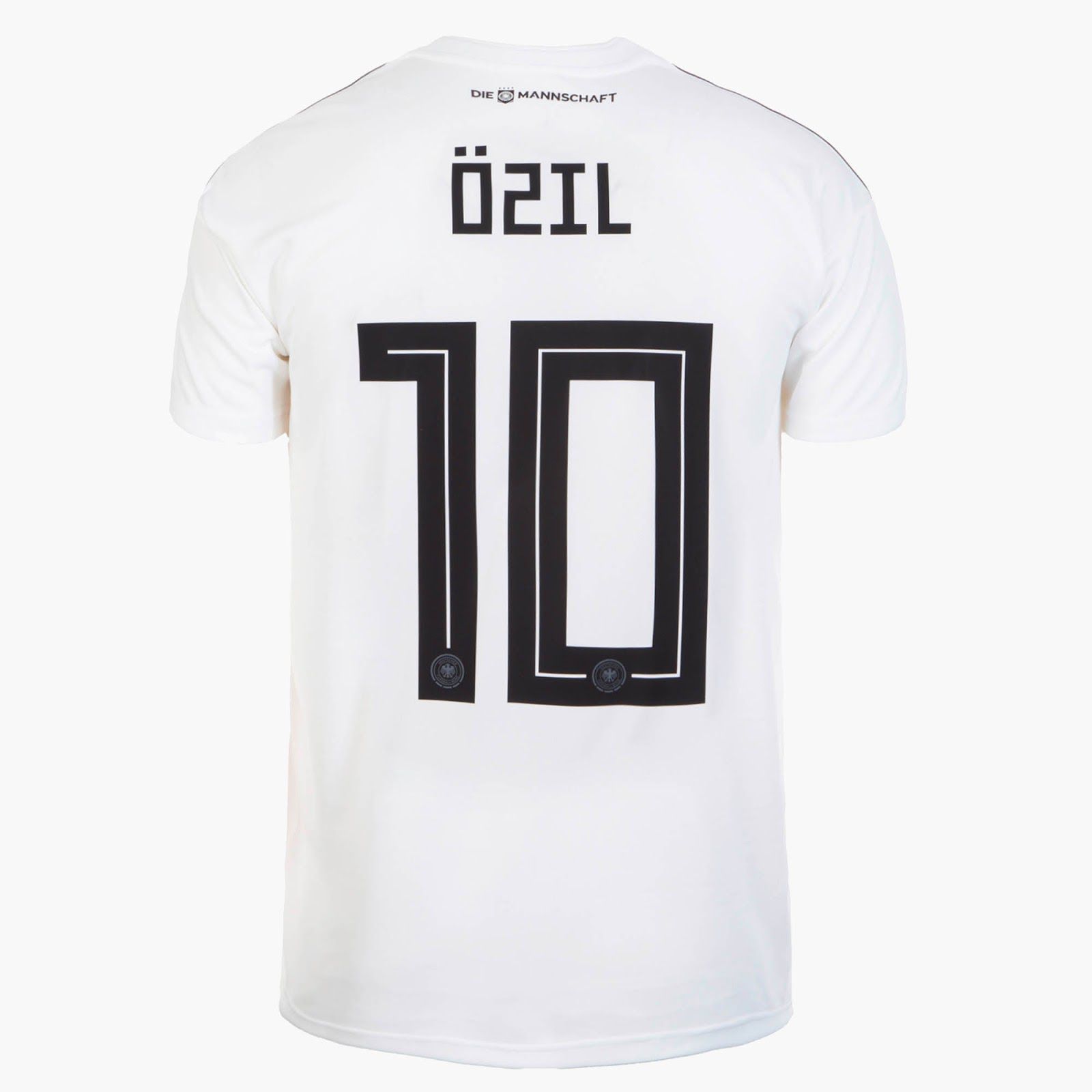
Il font di adidas per il Mondiale Insieme alle nuove magliette è arrivato anche il nuovo font d'ispirazione sovietica
La scorsa settimana adidas ha presentato le maglie delle nazionali per il prossimo mondiale di Russia 2018 e questo weekend le nuove divise hanno esordito tra playoff e amichevoli. I design delle nuove divise hanno tutte un gusto nostalgico, riprendendo le maglie storiche degli anni '80 e '90, quella della Spagna ha fatto addirittura scoppiare un caso nazionale per il blu usato nella fantasia. Tuttavia, uno dei particolari che viene più apprezzato dai fanatici come noi di maglie da calcio è il font usato per nomi e numeri delle magliette, e quello scelto da adidas per le sue maglie del Mondiale non passa certo inosservato.
Il font ha uno stile austero e spigoloso, si ispira all'alfabeto cirillico e all'immaginario sovietico. Le forme delle lettere e i numeri non hanno curve, solo angoli a 90 gradi. Una linea passa nel mezzo dei numeri, riducendo un po' il "peso" della figura, mentre le lettere rimangono piene.